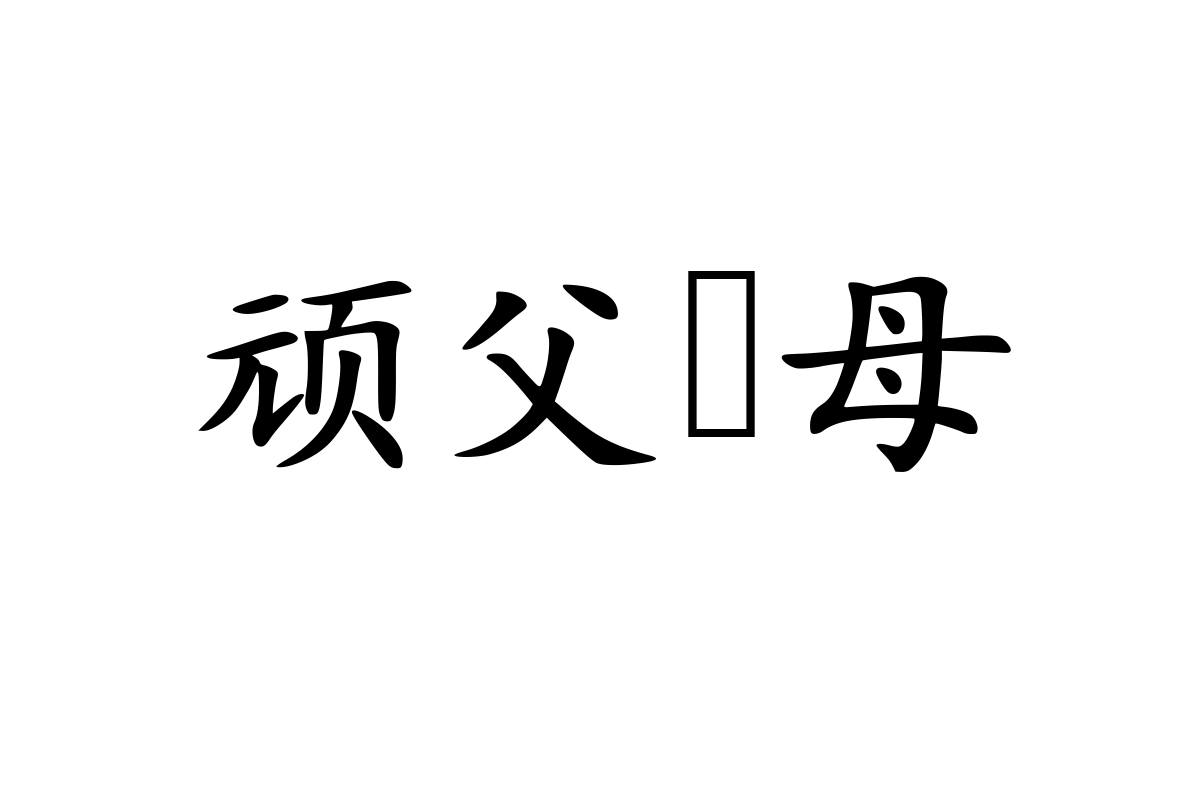
兰米粗楷是一套由日本设计师田中一郎(Yoshio Tanaka)设计的书法字体。这套字体以其独特的风格和强烈的视觉冲击力而闻名,被认为是现代书法字体的代表之一。
兰米粗楷的特点如下:
1. 字形:兰米粗楷的字形饱满、有力,笔画粗细分明,给人一种强烈的视觉冲击感。它的字形结构紧凑,线条流畅,具有很强的表现力。
2. 风格:兰米粗楷的风格独特,既有传统书法的韵味,又具有现代艺术的感觉。它融合了日本书法的简洁、明快的特点,以及西方现代设计的理念,形成了一种全新的设计风格。
3. 应用:兰米粗楷广泛应用于各种印刷品、广告、海报、包装等设计领域。它不仅适用于商业宣传,也适用于个人艺术作品的创作。
4. 评价:兰米粗楷受到了广泛的好评,被认为是现代书法字体中的佳作。它的出现,为现代书法字体的发展注入了新的活力,推动了书法字体的创新和发展。